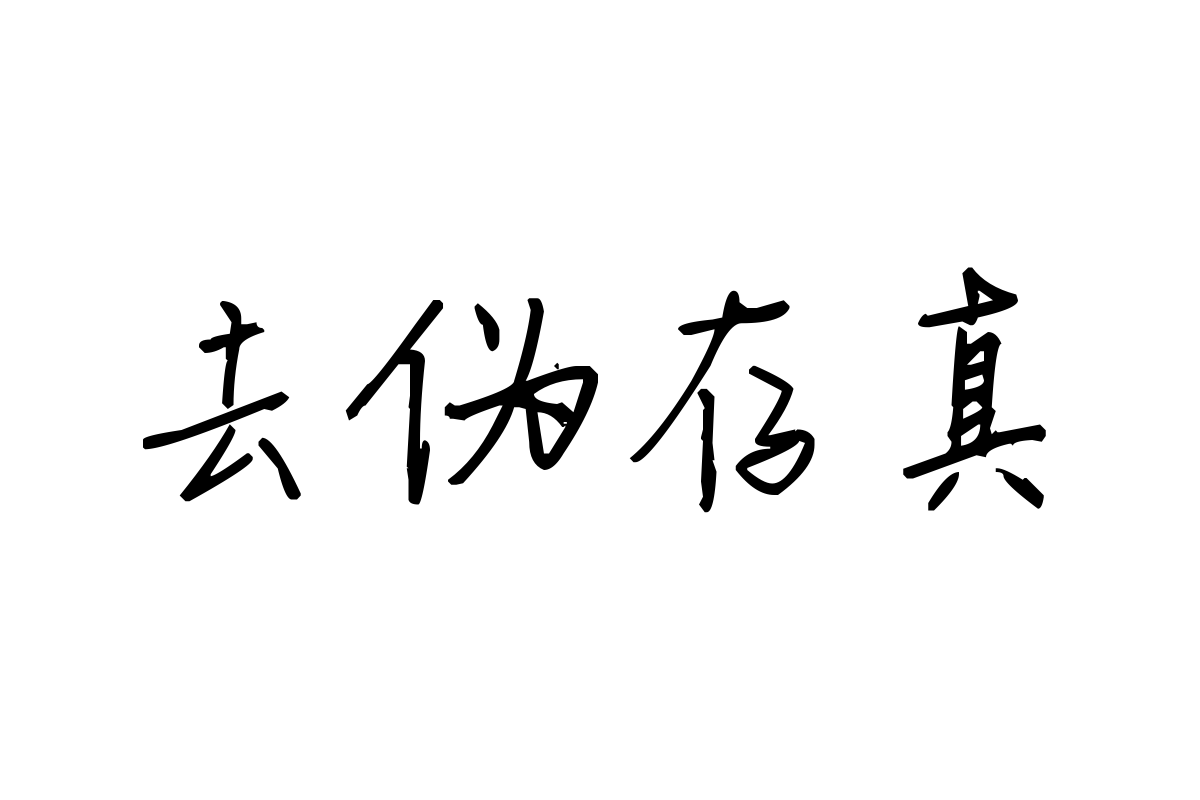
米开落笔成诗是一款书法字体,由米开文设计。这款字体具有独特的风格和特点,包括:
1. 字形独特:米开落笔成诗的字形独特,线条流畅,结构严谨,给人一种古朴典雅的感觉。
2. 笔画流畅:这款字体的笔画流畅,书写起来轻松自如,给人一种舒适的感觉。
3. 字体美观:米开落笔成诗的字体美观大方,适合用于各种场合,如书籍、报纸、广告等。
总之,米开落笔成诗是一款非常实用的书法字体,适合用于各种需要文字展示的场景。